LINE@のモニター企画、今回は3番目にご応募いただいた益田さんです!
書いていただいたのが、こちら。
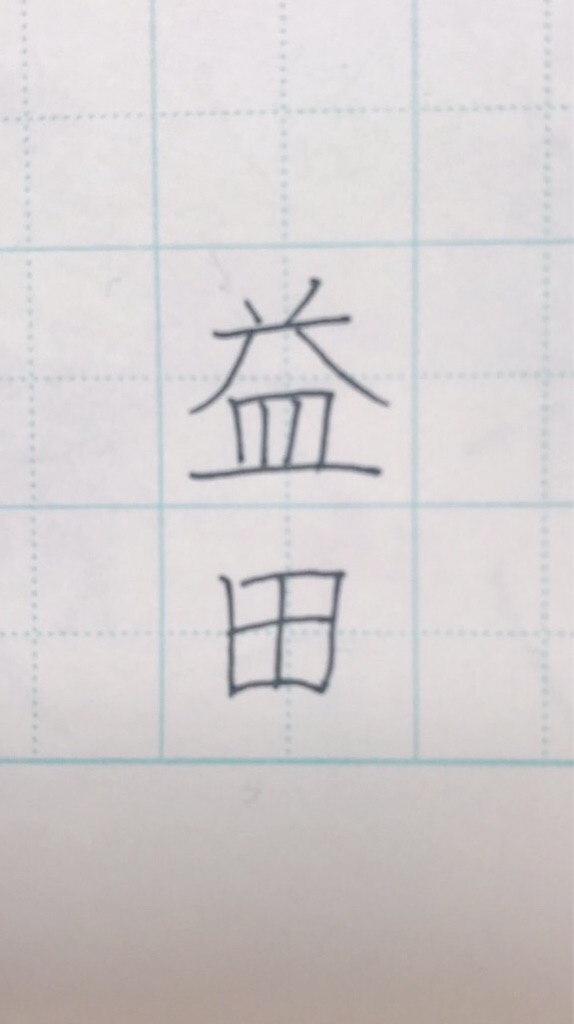
○良いところ
一画一画、とても丁寧な楷書で書かれています。形もほとんど崩れていませんので、少しの修正で正しい字形が習得できると思います。
◎改善点
中心が少しずれているので、まずは中心を捉えることから。皿や田の両端の縦画をキュッと内に入れると、文字が引き締まった印象になります。
中心を意識して、こんな感じに添削をさせていただきました。
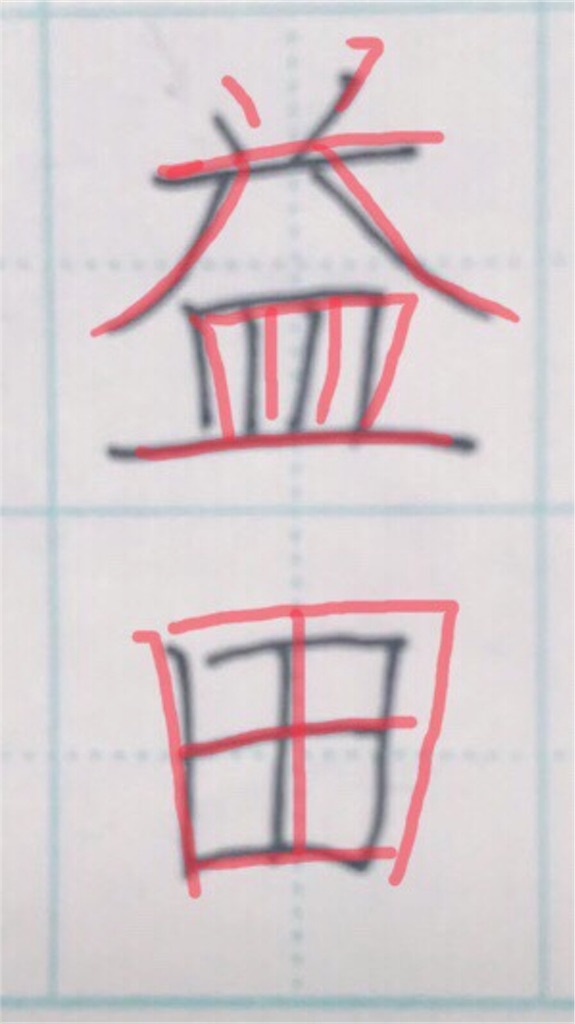
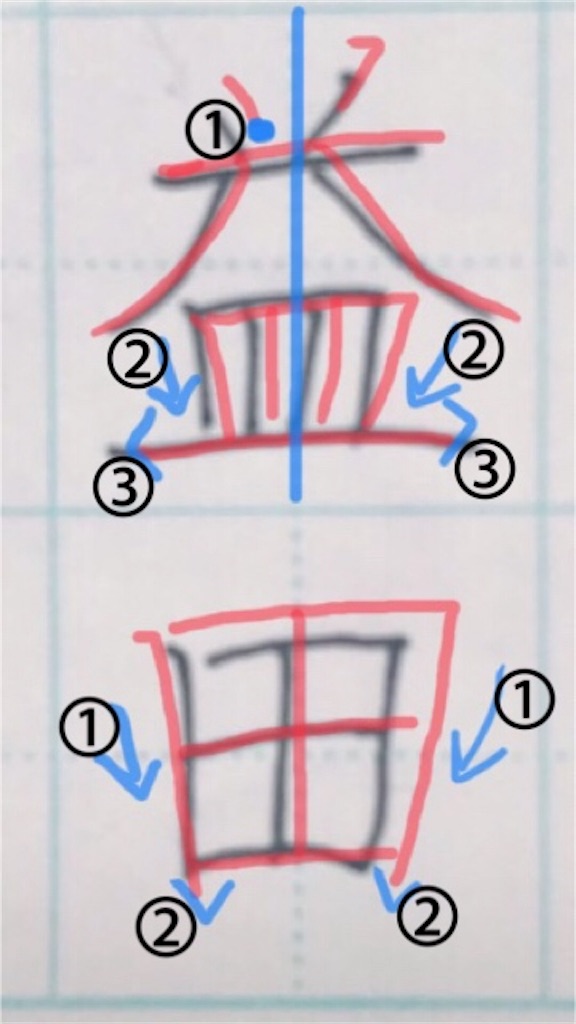
〈益〉
☆中心の確認。1、2画目の間。皿の真ん中(8画目と9画目の間)。
➀1画目は下の横画にくっつかないように。「美」「様」「並」なども同様です。
➁両端の縦画は内に入れると◎。
➂左右払いを強調するために、最終画は少し短く。(左右払いも思い切って、広げると◎)
〈田〉
➀こちらも、縦画を内に入れると◎。
➁縦画を下に出します。
☆一回り大きく書くと益とのバランスが取れます。
以上が添削ポイントです。
見本を書いてみました。
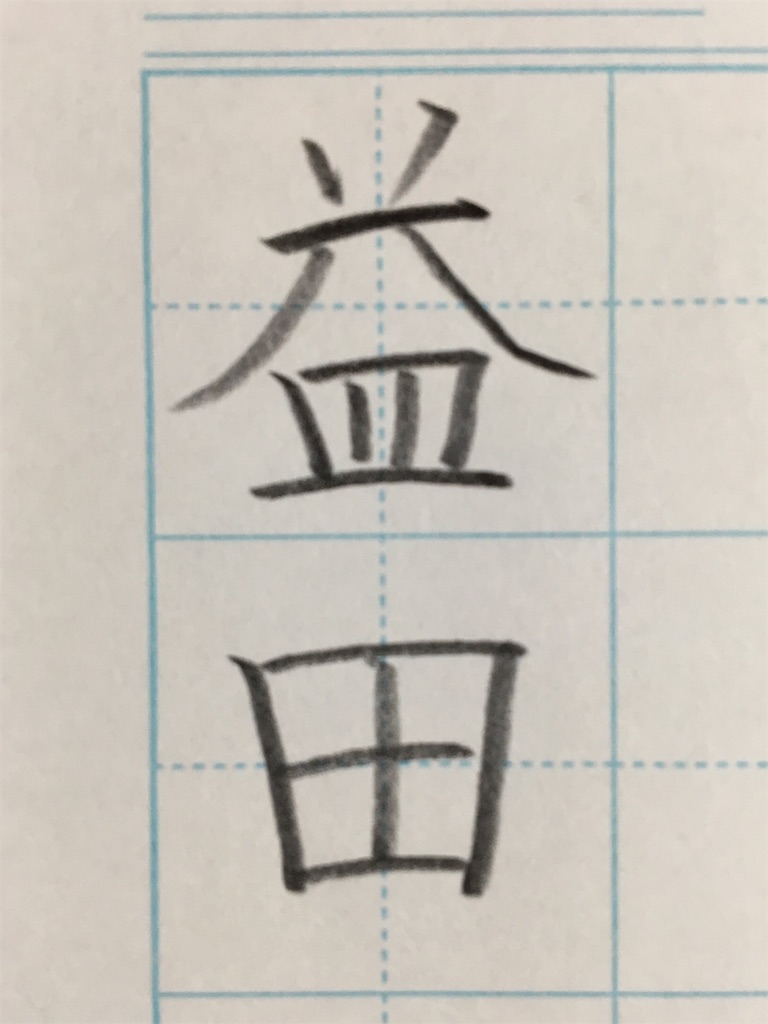
大まかなポイントを図説しました。